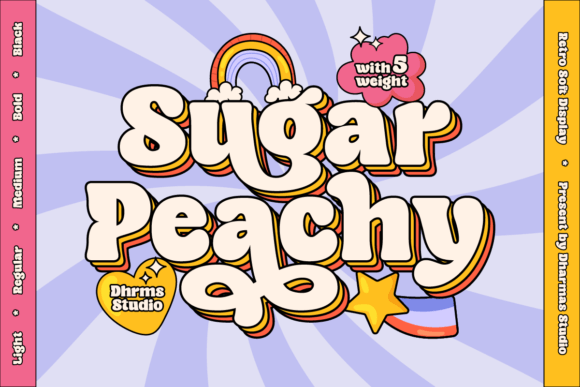
Sugar Peachy
Se você está procurando ativos de alta qualidade como Sugar Peachy, este pacote premium é uma escolha fantástica para seus projetos criativos.